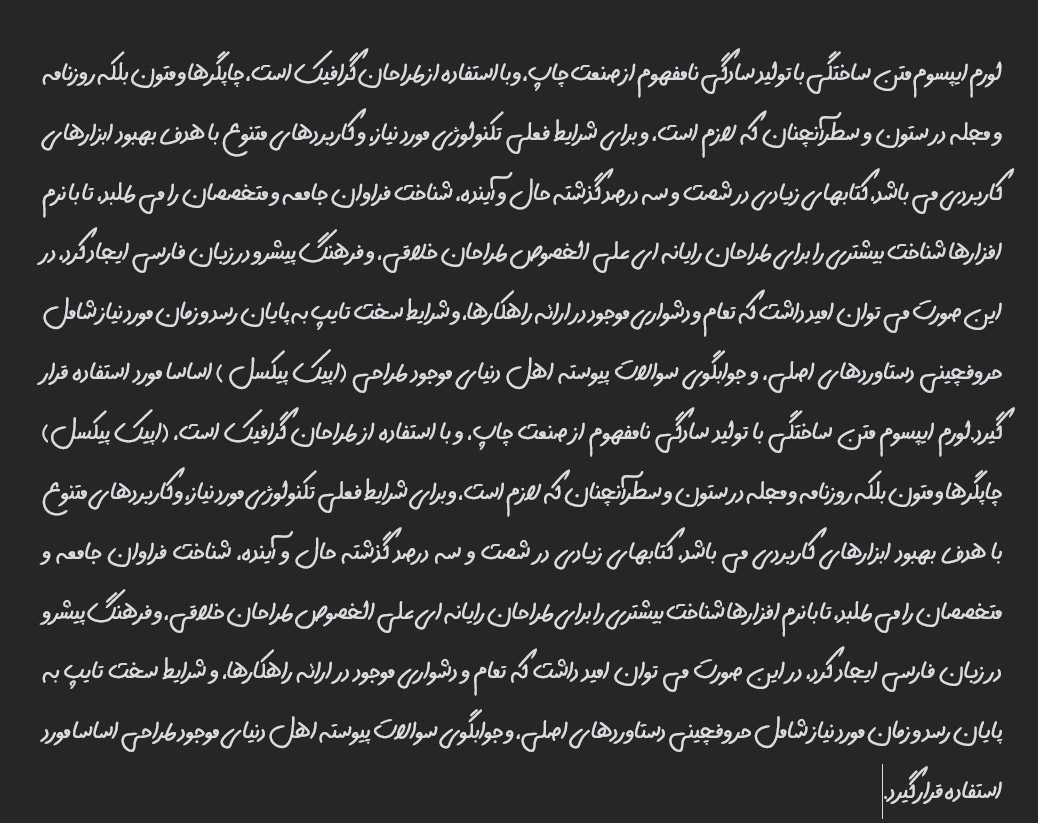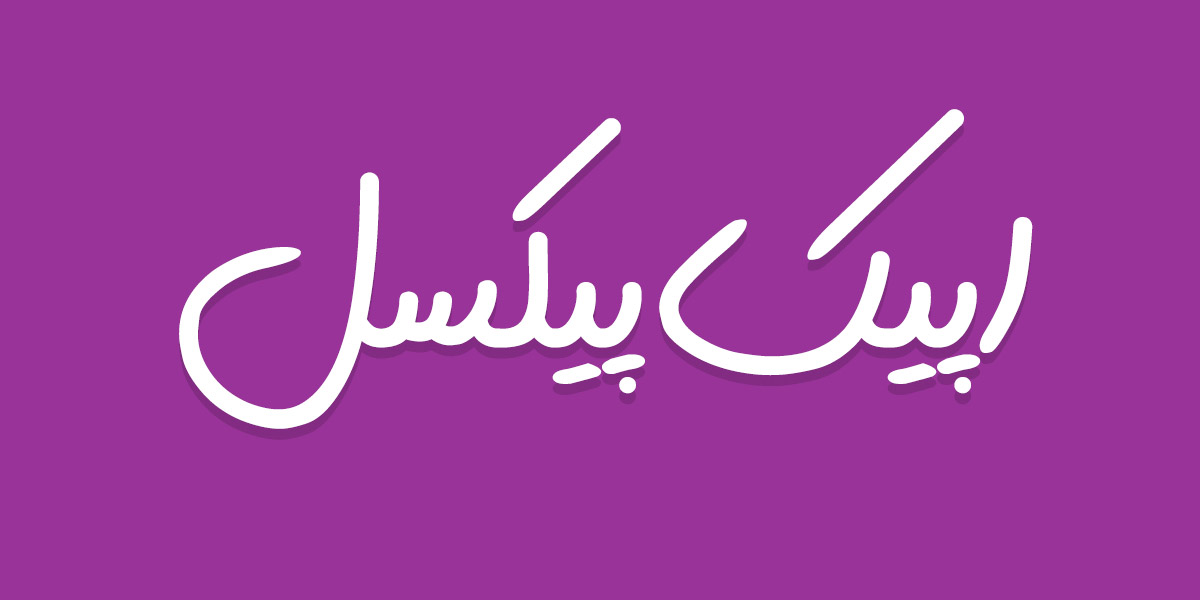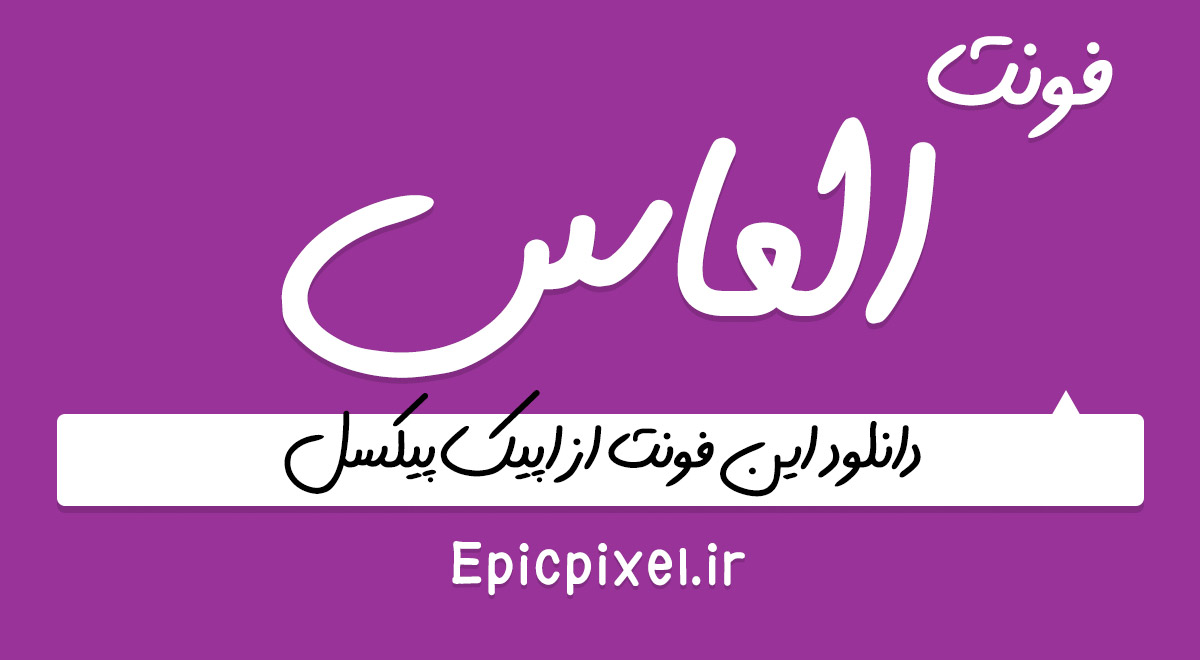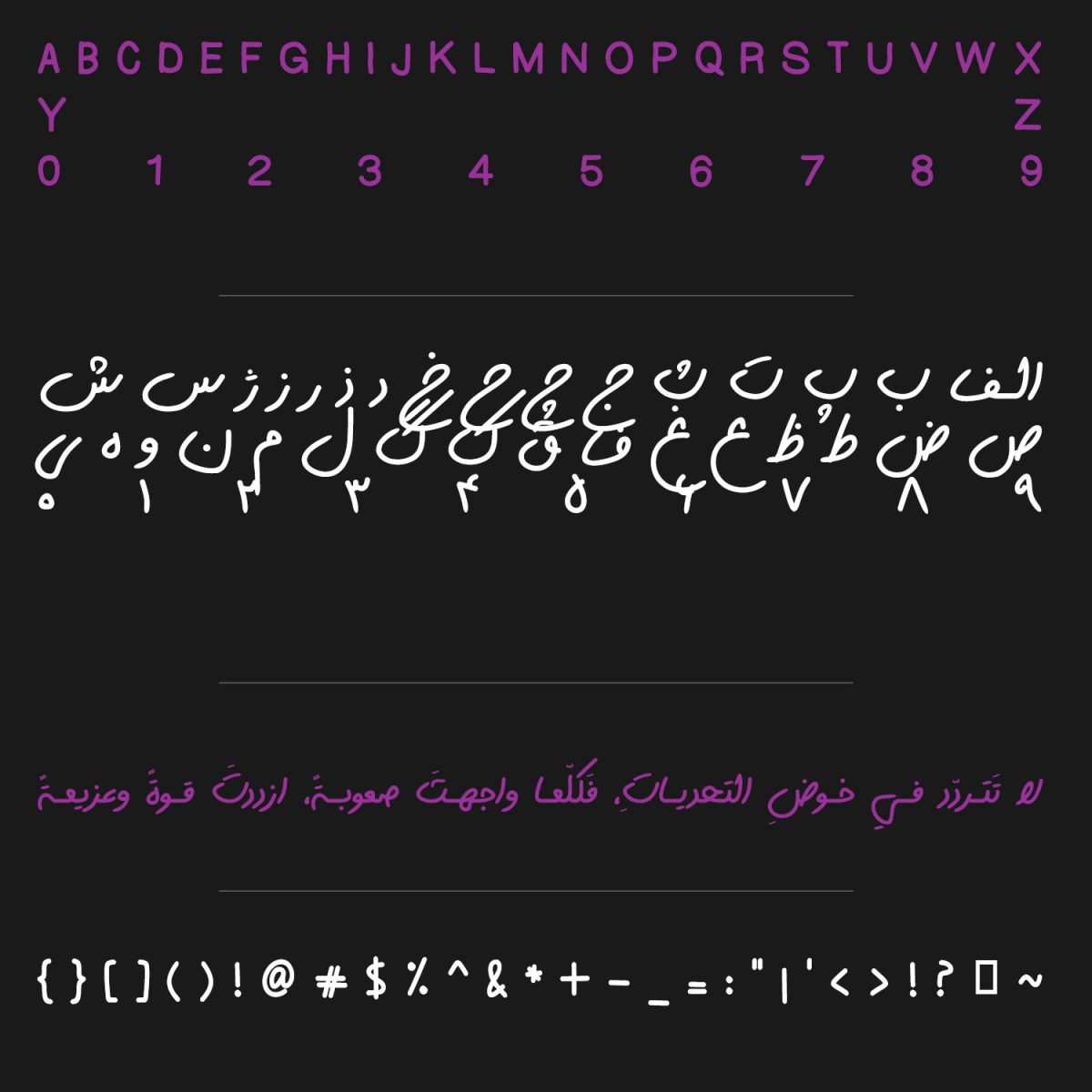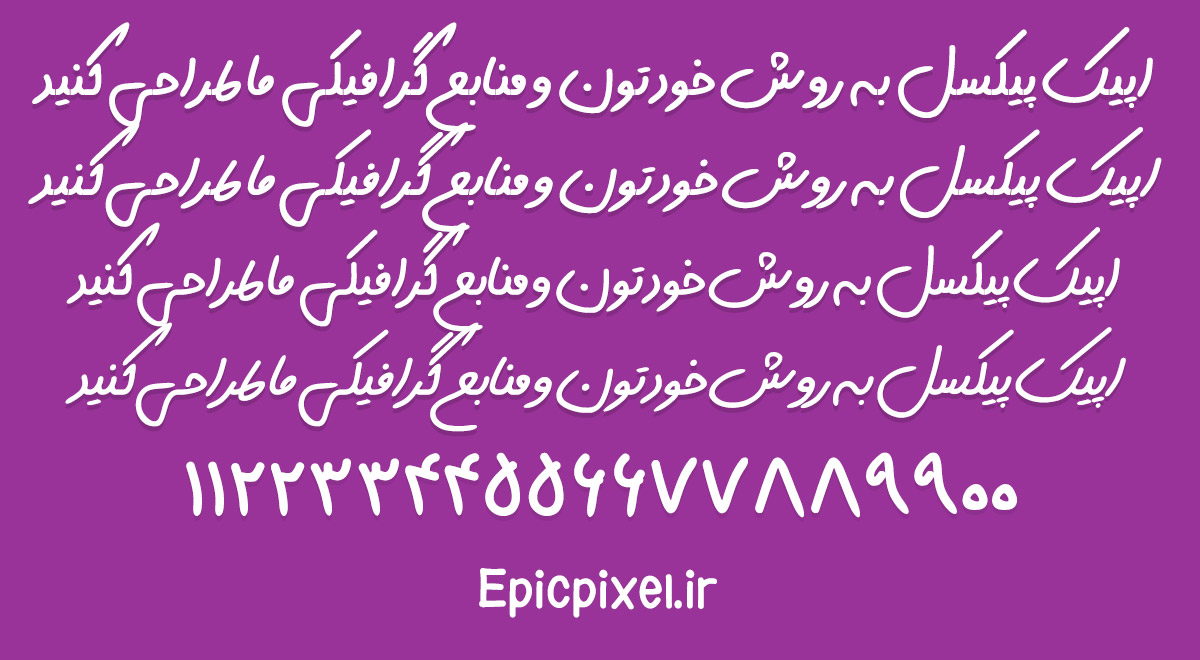
2 فونت الماس فارسی Almas
دانلود رایگان فونت دست نویس الماس، قلمی فارسی و دست نویس است که از دستخط یک طراح مشخص الهام گرفته و توسط یک تیم طراحی توسعه یافته است. این قلم زیبا با شخصیت روان، ساده، عاشقانه و با طراوت، دارای حروف بسیار نرم، کشیده، زیبا، کرنینگ متعادل، اعراب هوشمند و حروف و کلمات جایگزین متنوع می باشد. این بسته شامل نسخه اصلی فونت الماس و نسخه مشابه با نام دی جی الماس (Digi Almas) است که از نظر بصری کاملاً مشابه هستند. فونت الماس شامل حروف و اعداد فارسی و انگلیسی، و پشتیبانی از زبان های کردی و عربی است. این قلم زیبا به صورت رایگان برای دانلود در دسترس بوده و قابل استفاده در تمامی برنامه ها (ویندوز، iOS، اندروید) برای انواع طراحی گرافیک، عکس نوشته و محتوای شبکه های اجتماعی است.
فونت دست نویس الماس: قلمی روان و رایگان با زیبایی دستخط
فونت دست نویس الماس (Almas)، یک قلم فارسی و دست نویس است که قدرت و زیبایی خود را از روی دست خط سرکار خانم طیبه مرادی گرفته و توسط گروهی از طراحان توسعه و بازطراحی داده شده است. این فونت حرفه ای با دقت و حساسیت خاصی طراحی شده تا شباهت زیادی با دستخط اصلی داشته باشد و حس و حال یک دستخط طبیعی را منتقل کند.
شخصیت و روحیه این قلم روان ، ساده ، عاشقانه و با طراوت است که می تواند به راحتی در قالب آثار هنری جای گرفته و خودنمایی کند و آثاری شیک و بدیع خلق نماید. دارای حروف بسیار نرم ، کشیده ، زیبا است و زیبایی فونت در تصاویر کاملا مشخص هستند. حروف فونت دستنویس الماس روان، ساده و با طراوت طراحی شده اند که حس آرامش را به مخاطب منتقل می کند و این فونت انتخابی خوبی برای هنرمندان و طراحان سخت گیر است که به دنبال فونتی خاص و نوآورانه برای آثار خود هستند. این فونت دارای کنتراست و ضخامت خوبی است که شباهت آن به یک متن دست نویس را بیشتر می کند و خطوطی روان و تمیز دارد. ویژگی هایی مانند استایل و چیدمان بهم ریخته و نامتوازن و اتصالات همسان ندارد، به ظاهر طبیعی و غیر ماشینی آن کمک می کند، در حالی که ترمینال های ابتدا و انتهای آن با دقت کار شده اند و از نظر طراحی قوی است.
فونت الماس شامل حروف انگلیسی و فارسی هر دو بحالت دستونیس و خوشنویسی است که امکان استفاده در متون دوزبانه و پروژه های بین المللی را فراهم می کند. این بدان معناست که حروف لاتین نیز با سبکی متناسب با دستخط اصلی طراحی شده اند. به طور خاص، دارای تمامی حروف فارسی، اعداد و نمادهای مورد استفاده در زبان فارسی می باشد. دارای حروف لاتین متناسب شده (به سبک دست نویس) و دارای اعداد فارسی متناسب با فونت است. از زبان کردی و عربی نیز پشتیبانی می کند که آن را برای پروژه های چندزبانه کاربردی می سازد و نیازهای مختلف طراحان را پوشش می دهد.
از نظر فنی، فونت فارسی الماس دارای کرنینگ متعادل (فاصله گذاری مناسب بین حروف) و اعراب هوشمند برای هر حرف است که خوانایی و زیبایی متن را بهبود می بخشد و دقت در نمایش اعراب را تضمین می کند. همچنین شامل حروف و کلمات جایگزین متنوعی است که برای خوانایی بهتر و زیباتر و طبیعی تر کردن شکل و فرم نوشته ها قرار گرفته است و براحتی می توانید از آن استفاده نمایید و به نوشته های خود تنوع ببخشید. راهنمای استفاده از حروف جایگزین نیز ارائه شده است.
این فونت دست نویس زیبا و حرفه ای با استفاده از تکنولوژی های مدرن طراحی شده و قابلیت تغییر اندازه بدون از دست دادن کیفیت را دارد، که آن را برای استفاده در اندازه های مختلف مناسب می سازد. قابل نمایش در همه نرم افزارهای طراحی و متون فارسی را دارا می باشد. این فونت حرفه ای مناسب استفاده در انواع طراحی های گرافیکی است و طراحان تمایل دارند به جای فونت های کلاسیک و رسمی، از فونت های دست نویس مانند الماس در آثار خود استفاده کنند و این فونت پاسخی به این نیاز است.
کاربردهای فونت دست نویس الماس در طراحی گرافیک و محتوای دیجیتال
با توجه به سبک دست نویس، روان، ساده و با طراوت، و قابلیت های فنی، فونت دست نویس الماس کاربردهای گسترده ای در طراحی گرافیک و تولید محتوای دیجیتال دارد. این قلم زیبا مناسب استفاده در استوری، عکسنوشته، تایپوگرافی های خلاقانه و پست های اینستاگرامی است که در آن ها جلوه های بصری و حس صمیمیت اهمیت دارد. همچنین برای شعار های تبلیغاتی خاص، جملات و عناوین تاکیدی، عاشقانه، احساسی، و جملات قصار به کار رفته در ادیتها و کلیپها کاربرد دارد. در جلد کتاب، مجلات، تراکت و بنرهای شبکه های اجتماعی و برای دلنوشته های عاشقانه و نقل قول های احساسی ، اخلاقی و فرهنگی استفاده می شود. در کلیپ ، تیزر ، موشن گرافیک و سایر محتواهای چند رسانه ای و در طراحی استوری ، پست و تولید محتوا در اینستاگرام ، تلگرام ، واتس آپ و سایر محتواهای گرافیکی و تصویری ، تکسنوشت و دلنوشته های احساسی و عاشقانه استفاده می شود. به طور کلی برای طراحی انواع امور گرافیکی به خصوص طراحی عکس نوشته و متون مختلف توسط طراحان فارسی زبان و در ایجاد طرح های تایپوگرافی (چیدمان حروف) مناسب است. این فونت در نرم افزار های با قابلیت تایپ در موبایل و در نرم افزار های دسکتاپ مانند فتوشاپ، پریمیر، افترافکت و ورد قابل استفاده است.